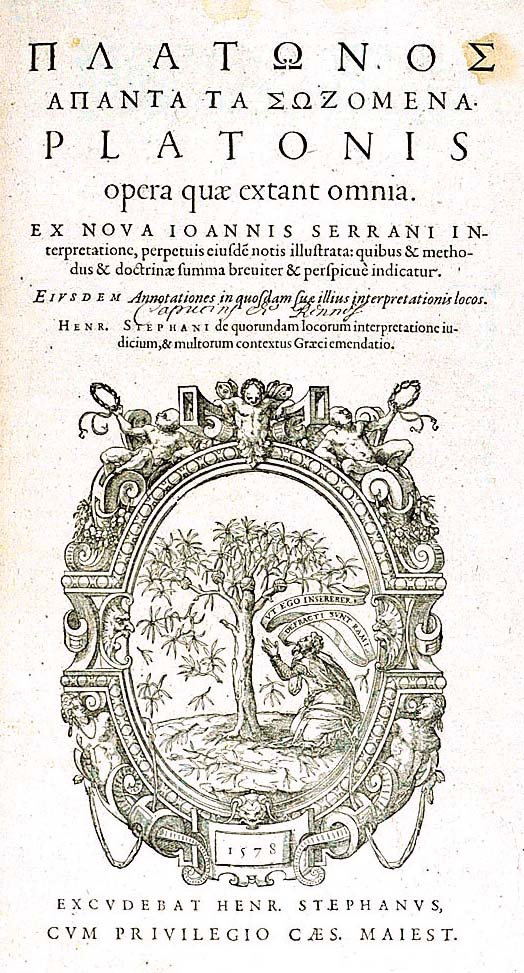
Robert Estienne, impressor e teólogo francêsRobert Estienne (Paris, 1503 Genebra, 1559) imprimiu obras em hebraico, grego e latim e 11 edições da Bíblia, destacando-se a que imprimiu em 1532, e o Novo Testamento em língua grega que saiu do prelo em 1550. Robert imprimiu cerca de 382 obras.
Foi a Robert Estienne que o rei François I concedeu, em 1528, o título honorífico de Impressor real. Robert Estienne, nome latinizado Stephanus, foi um tipógrafo e impressor parisiense do século XVI. Foi o primeiro a imprimir a Bíblia com a inclusão de capítulos e versículos numerados. Aprendeu o latim, o grego e o hebraico. Em 1526, quando passou a gerir a oficina tipográfica que pertencia ao seu pai, Robert já era reconhecido como um erudito de elevado padrão linguístico. Embora publicasse edições críticas da literatura latina e de outras obras eruditas, o seu grande interesse dirigia-se para a impressão da Bíblia. Robert Estienne tomou como objectivo restabelecer o melhor possível o texto original da Bíblia Vulgata latina de Jerónimo de Strídon, traduzida no século V.
Tipógrafo RealA engenhosidade e a habilidade linguística de Estienne não deixaram de ser notadas por François I, rei de França. Estienne recebeu o título de Typographus regius, permitindo-lhe traduzir e imprimir obras em latim, hebraico e grego. Nessas funções, Estienne produziu algumas das que até hoje são consideradas obras primas da tipografia francesa. Em 1539, começou a imprimir a primeira Bíblia hebraica completa impressa na França. Em 1540, introduziu ilustrações na sua Bíblia em latim. Mas, em vez das usuais apresentações fantasiosas de eventos bíblicos, comuns na Idade Média, Estienne usou gravuras instrutivas, baseadas em evidência arqueológica, ou em medidas e descrições encontradas no próprio texto bíblico. Estas gravuras xilográficas retratavam em pormenor assuntos tais como a Arca da Aliança, o vestuário do Sumo Sacerdote de Israel, o Tabernáculo e o Templo de Salomão. Nesta época, produziu numerosas edições de obras gramaticais e outros livros académicos, incluindo vários de Philipp Melanchthon e de escritores clássicos, tais como Dio Cassius, Eusébio de Cesareia, Cícero, Sallust, Júlio César, Junianus Justinus e Sozomen. Várias destas obras, especialmente as edições gregas, foram impressas com fontes produzidas por Claude Garamond, tornando-as famosas pela sua elegância tipográfica. Estienne passou a produzir também a primeira edição crítica do Novo Testamento, ou seja, das escrituras gregas cristãs. Embora as primeiras duas impressões do texto grego feitas por Estienne similares à obra de Desidério Erasmo, Estienne acrescentou na terceira edição, de 1550, as citações e as remissões de cerca de 15 manuscritos, inclusive do Códice Bezace do século V e da Septuaginta.
Esta edição feita por Estienne teve tão ampla aceitação, que se tornou a base do chamado Textus Receptus, ou Texto Recebido, em que se basearam muitas das traduções posteriores, inclusive a versão do português João Ferreira de Almeida, de 1681. Em Novembro de 1550, Estienne mudou-se para Genebra, na Suíça. O corpo docente tornara ilegal na França publicar qualquer Bíblia a não ser a Vulgata. Estienne reimprimiu o seu "Novo Testamento" grego em 1551, com duas versões latinas, a Vulgata e o texto de Erasmo, em colunas paralelas. Acompanhou essa tarefa em 1552 com uma tradução francesa das Escrituras Gregas em colunas paralelas, com o texto latino de Erasmo. Nestas duas edições, Estienne introduziu o sistema de dividir o texto bíblico em versículos numerados o mesmo sistema hoje usado universalmente. Embora outros já antes tivessem tentado sistemas diferentes para a separação em versículos, o de Estienne tornou-se a forma aceita. A Bíblia que publicou em francês, de 1553, foi a primeira Bíblia completa com o seu sistema de separação por versículos. Estienne, decidido a colocar sua erudição à disposição de outros, dedicou sua vida à divulgação da Bíblia. Pouco antes da sua morte, em 1559, Estienne trabalhava numa nova tradução das Escrituras Gregas. Perguntaram-lhe: "Quem a vai comprar? Quem a vai ler?" Ele respondeu: "Todos os homens instruídos de devoção piedosa." Henry, Robert, e FrançoisTrês filhos de Robert Estienne, Henry, Robert, e François, tornaram-se tipógrafos ou impressores famosos. François, o terceiro filho, nascido em 1540 possuía a sua própria tipografia em Genebra, entre 1562 e1582, imprimindo numerosas edições da Bíblia em Latim e Francês, bem como algumas obras de Calvino. Alguns escritores franceses identificam-no com um tipógrafo de apelido Estienne, existente na Normandia para onde François alegadamente emigrou em 1582. Robert, o segundo filho (15301570), começou o seu trabalho em Paris, por sua própria conta em 1556, e em 1563, tal como havia acontecido com o seu pai, recebeu o título de Typographus regius. Envolveu-se especialmente na impressão de obras civis, não religiosas. Manteve-se fiel à Igreja Católica, recebendo assim o apoio de Carlos IX, conseguindo assim, por volta de 1563, restabelecer a tipografia do seu pai em Paris. A reimpressão que efectuou do Novo Testamento editado anteriormente pelo seu pai, similar em qualidade e elegância, é agora extremamente rara e valiosa. Até 1861, com Antoine Estienne, os Estienne dedicaram-se à tipografia. Em homenagem a esta família de tipógrafos ilustres foi fundada em 1889, em Paris, a prestigiosa Escola Estienne. þ Linkswww.bvh.univ-tours.fr/resauteur.asp?auteur=Estienne,%20Robert%20I&ordre=titre Estienne, Robert, - Les mots francois selon l'ordre des lettres, ainsi qu'il les faut escrire, tournez en latin, 1582. http://bibliotecadigital.fl.ul.pt/ BibliografiaHeitlinger, Paulo. Tipografia: origens, formas e uso das letras. Copyright © 2006 Paulo Heitlinger, ISBN 10 972-576-396-3 , ISBN 13 978-972-576-396-4, Depósito legal 248 958/06. Dinalivro. Lisboa, 2006. WikipediaA cópia de partes deste artigo na Wikipedia é ilegal, não foi autorizada! Página actualizada em 2011. |